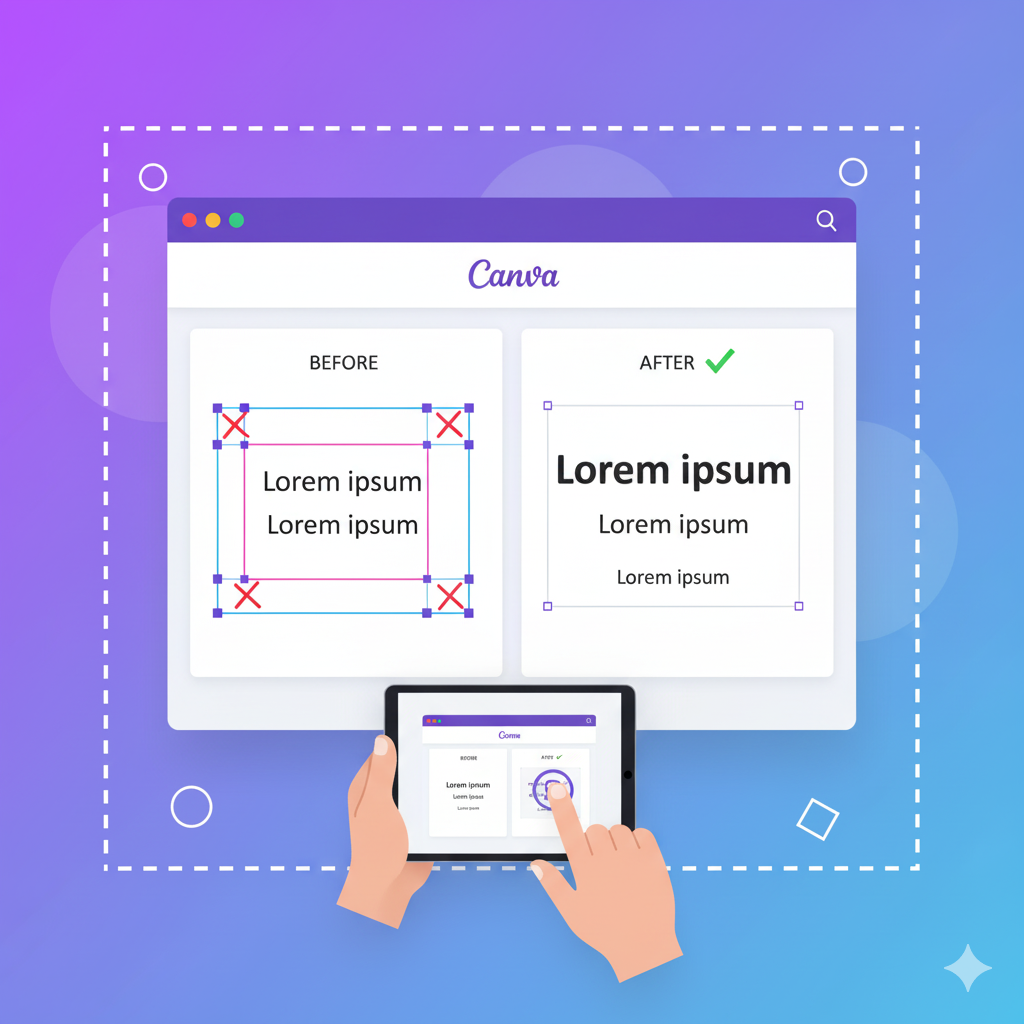
Trik Menyesuaikan Ukuran Font Secara Proporsional
Gubuku – Ukuran font proporsional adalah ukuran huruf yang disesuaikan agar memiliki keseimbangan visual dengan elemen lain dalam desain, seperti judul, subjudul, dan isi teks. Font yang proporsional tidak terlalu besar atau kecil, sehingga tetap nyaman dibaca tanpa mengganggu tampilan keseluruhan desain.
Menurut Canva Design School (sumber: canva.com/learn/typography), keseimbangan ukuran font sangat memengaruhi hierarki visual. Dengan proporsi yang tepat, mata pembaca dapat dengan mudah mengenali bagian mana yang paling penting dalam desain.
Sebagai contoh, jika kamu membuat poster, judul sebaiknya memiliki ukuran yang lebih besar dibandingkan isi teks, tetapi tidak sampai mendominasi seluruh ruang.
Pentingnya Menyesuaikan Ukuran Font Secara Proporsional
Ukuran font yang tidak proporsional dapat membuat desain terlihat tidak seimbang. Misalnya, teks terlalu kecil akan sulit dibaca, sementara teks terlalu besar bisa terlihat berlebihan dan mengganggu fokus pembaca.
Beberapa alasan pentingnya menyesuaikan ukuran font secara proporsional:
1. Meningkatkan keterbacaan (readability).
Ukuran font yang pas memudahkan audiens membaca teks tanpa merasa lelah.
2. Menjaga hierarki visual.
Dengan proporsi yang baik, pembaca langsung tahu mana bagian penting seperti judul, subjudul, dan isi.
3. Menampilkan kesan profesional.
Desain yang proporsional menunjukkan perhatian terhadap detail dan estetika.
4. Menyesuaikan dengan konteks media.
Ukuran font untuk website tentu berbeda dengan ukuran font di poster atau feed Instagram.
Seperti dijelaskan oleh Adobe Fonts (sumber: fonts.adobe.com), font yang proporsional membantu pesan tersampaikan dengan lebih efektif, karena teks mudah dipahami dan enak dilihat.
Rasio dan Skala Ukuran Font
Salah satu trik menyesuaikan ukuran font secara proporsional adalah menggunakan rasio atau skala tipografi. Skala ini digunakan untuk menentukan seberapa besar perbedaan antara ukuran teks satu dengan yang lain.
Beberapa skala yang umum digunakan oleh desainer profesional:
Jenis Skala Rasio Umum Contoh Ukuran (px)
Minor Third 1.2 12, 14.4, 17.3, 20.7, 24.9
Major Third 1.25 12, 15, 18.8, 23.4, 29.3
Perfect Fourth 1.333 12, 16, 21.3, 28.4, 37.8
Golden Ratio 1.618 12, 19.4, 31.4, 50.8, 82.2
Sumber: Type Scale Guide by Modular Scale (https://type-scale.com)
Gunakan rasio ini agar ukuran font terlihat serasi. Misalnya, jika teks utama kamu berukuran 16px, maka subjudul bisa dibuat sekitar 20–24px dengan rasio major third.
Tips Menentukan Ukuran Font yang Ideal
Berikut beberapa trik mudah untuk menyesuaikan ukuran font secara proporsional tanpa harus bingung menghitung:
1. Gunakan Hierarki Teks
Mulailah dari menentukan ukuran teks utama (body), lalu kembangkan ukuran lain berdasarkan itu. Misalnya:
1. Body text: 16px
2. Subjudul: 24px
3. Judul utama: 36px
Dengan hierarki seperti ini, pembaca langsung tahu bagian mana yang harus diperhatikan terlebih dahulu.
2. Sesuaikan dengan Media
Ukuran font di layar HP tentu berbeda dengan di spanduk besar.
1. Untuk website/blog: body 16–18px, heading 28–36px.
2. Untuk poster: judul bisa 60–100px tergantung ukuran kanvas.
3. Untuk media sosial: teks sebaiknya tidak lebih kecil dari 20px agar tetap terbaca di layar kecil.
3. Gunakan Grid dan Margin
Gunakan grid atau garis bantu agar jarak antar elemen tetap seimbang. Dengan cara ini, ukuran font akan tampak lebih proporsional terhadap ruang desain.
4. Coba Kombinasi Font yang Serasi
Ukuran font juga dipengaruhi oleh bentuk hurufnya. Misalnya, font Serif seperti Times New Roman terlihat lebih kecil dibanding Sans Serif seperti Arial pada ukuran yang sama.
Menurut Envato Tuts+ (sumber: tutsplus.com), penting untuk menyesuaikan ukuran font agar dua jenis huruf berbeda tetap terlihat harmonis.
Trik Profesional: Gunakan “Optical Balance”
Desainer profesional sering menggunakan prinsip optical balance, yaitu menyesuaikan ukuran font bukan hanya berdasarkan angka, tapi juga berdasarkan persepsi visual.
Contohnya, dua font dengan ukuran sama (misal 20px) bisa tampak berbeda besar karena perbedaan gaya desain font-nya. Jadi, sesuaikan berdasarkan penampilan visual di layar, bukan hanya ukuran numerik.
Kamu bisa melakukan ini dengan langkah berikut:
1. Letakkan teks dalam desainmu.
2. Bandingkan antar elemen.
3. Atur ukuran sedikit demi sedikit sampai terlihat seimbang.
Metode ini sangat efektif digunakan di Canva, Figma, atau Photoshop karena kamu bisa melihat hasilnya secara langsung.
Menyesuaikan Ukuran Font untuk Desain Digital
Untuk konten digital seperti website, postingan Instagram, atau presentasi PowerPoint, ukuran font yang proporsional membantu tampilan tetap enak dilihat di berbagai perangkat.
Menyesuaikan ukuran font secara proporsional adalah langkah penting dalam desain agar hasil akhirnya tampak profesional, mudah dibaca, dan enak dipandang.
Beberapa hal penting yang perlu kamu ingat:
1. Tentukan skala tipografi yang konsisten.
2. Sesuaikan ukuran dengan konteks media.
3. Gunakan prinsip optical balance agar tampak seimbang secara visual.
4. Hindari penggunaan ukuran ekstrem yang mengganggu keterbacaan.
Dengan memahami trik ini, kamu tidak hanya bisa membuat desain yang indah, tetapi juga mampu menyampaikan pesan dengan lebih efektif.